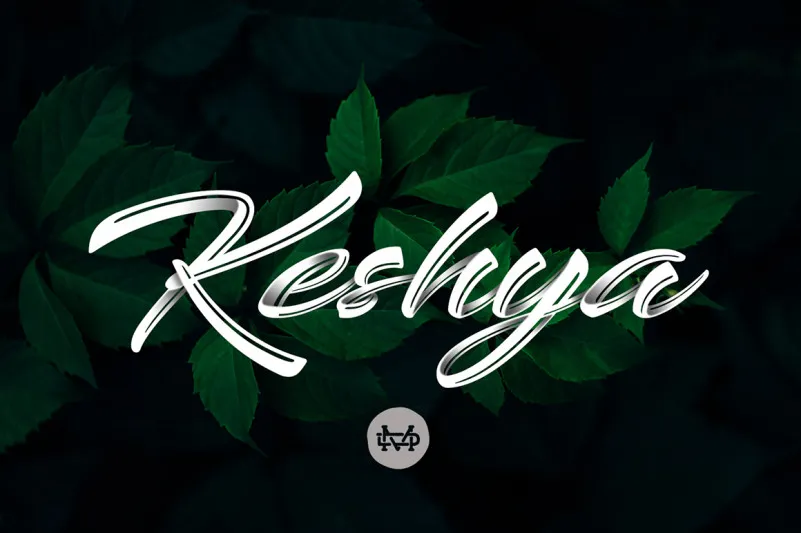
Keshya Brush Font – Download Grátis
A fonte Keshya Brush Font é uma escolha perfeita para designers que buscam algo único e vibrante. Ela é uma fonte feita à mão em estilo esquisito, com um tom poderoso e moderno que cria um aspecto autêntico sem precisar de muito trabalho adicional. Ideal para estilos como ilustrações ou desenhos digitais, Keshya Brush Font adiciona uma nota vibrante a qualquer projeto. Feita pelo designer madeDeduk, esta fonte oferece uma experiência intuitiva e fácil de usar, garantindo que qualquer design idea seja transformada em um verdadeiro destaque no momento da criação.